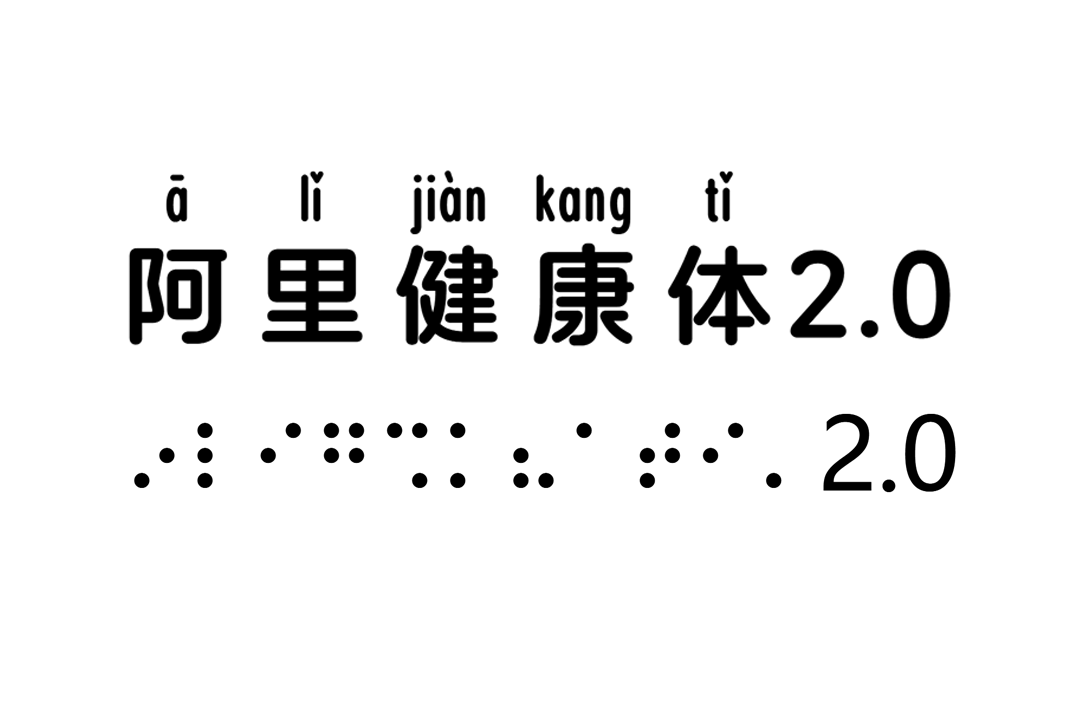
非盲文专业人士使用盲文字库时需搭配拼音字库使用,需秉持对待盲人的尊重和社会责任感,认真阅读现行盲文规范,咨询盲文专业人士,以保证盲文内容的正确性。
阿里健康体2.0家族字体是阿里健康设计与方正字库共同设计开发的,于2023年11月正式发布;是首款中文盲文注音定制字体。
该字体以无障碍设计为初衷,以服务于视障人士为目标,为了鼓励更多人关注无障碍设计,进一步推进医疗健康服务的普惠可及,阿里健康体2.0面向全社会(包括商业企业)永久免费开放使用,希望通过技术公益,推动无障碍环境建设,传递现代设计的人文关怀。